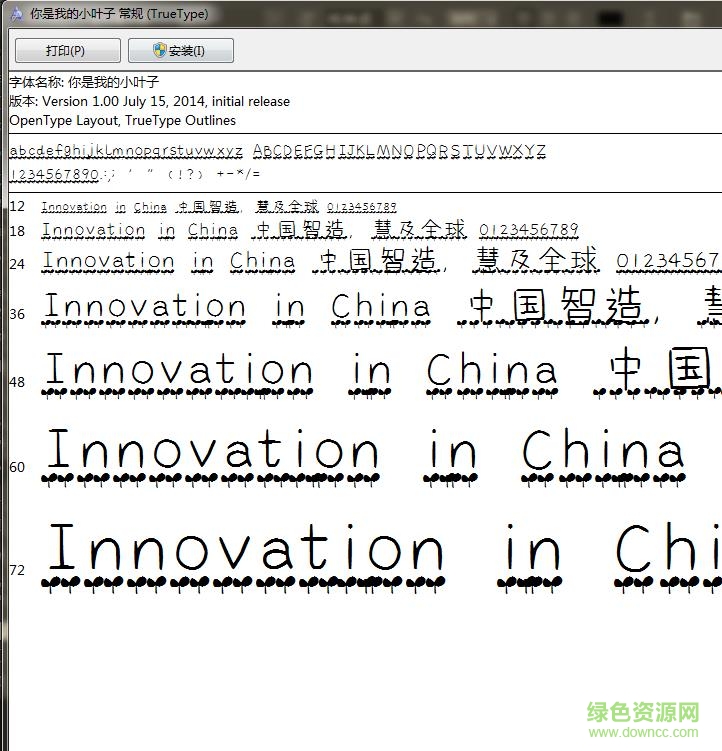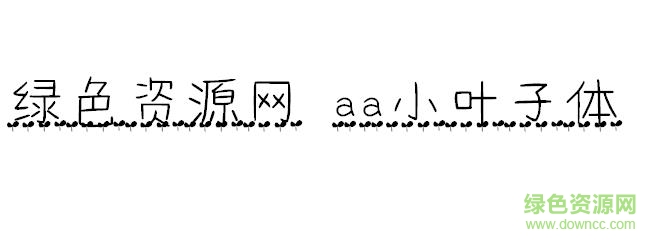
小葉子小隊(duì)美化字體是一款很不錯(cuò)的字體呢,擁有很清新的字體風(fēng)格,很適合女生使用,這款字體在手機(jī)上電腦都能夠達(dá)到很好達(dá)到顯示效果,如在華為手機(jī)中進(jìn)行聊天文字輸入,在電腦上進(jìn)行藝術(shù)字自作等,快來綠色資源網(wǎng)下載吧!